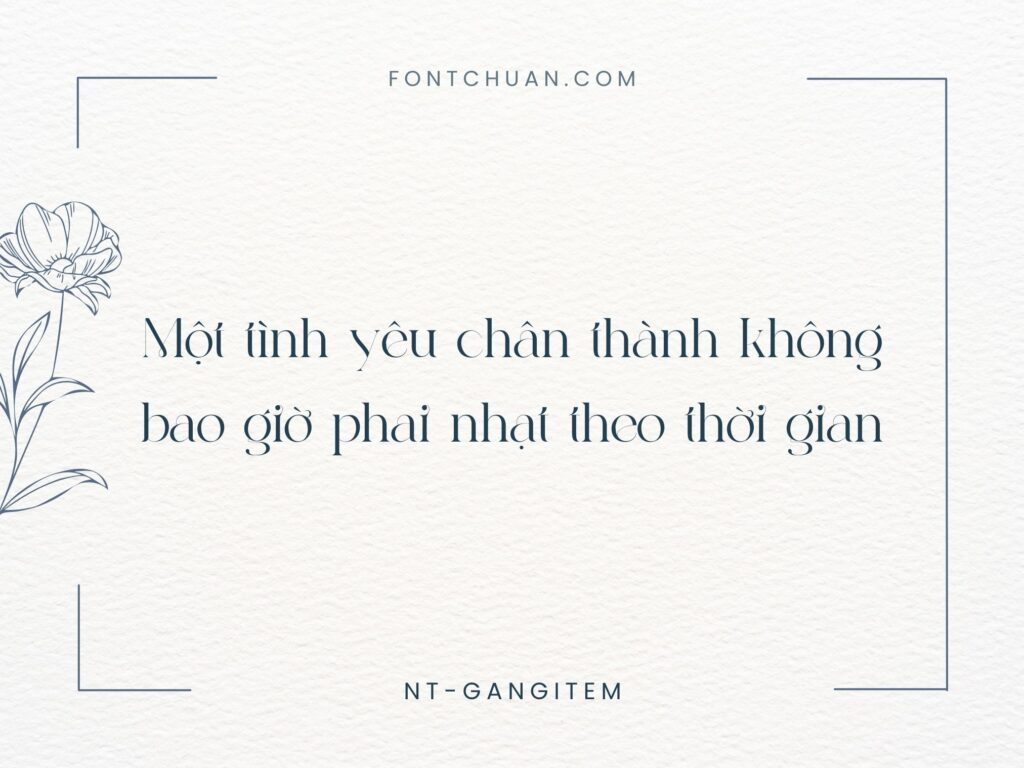
Font Gangitem Việt Hóa
Gangitem là một font serif hiện đại và thanh lịch, được thiết kế bởi 177Studio. Font này được trang bị nhiều ligature tùy ý, mang đến sự đa dạng và tinh tế trong thiết kế typography. Gangitem không chỉ là một Font Display lý tưởng cho các tiêu đề, logo, trích dẫn nổi bật mà còn có thể được sử dụng như một Font chữ thiệp cưới sang trọng, tạo vẻ đẹp tinh tế và lãng mạn cho các thiết kế thiệp mời, thiệp cưới hoặc các ấn phẩm sự kiện đặc biệt. Font này hỗ trợ tiếng Việt và nhiều ngôn ngữ khác, được sưu tầm và đăng bởi thành viên của Font Chuẩn.
Font có cấu trúc chữ rõ ràng, các đường nét tinh tế và độ dày nét đa dạng, tạo nên sự cân bằng giữa tính thẩm mỹ và khả năng đọc. Gangitem phù hợp cho các thiết kế thiệp mời, logo, tiêu đề và các ấn phẩm truyền thông. Các ngành nghề như quảng cáo, thiệp cưới, giáo dục và bất động sản có thể tận dụng hiệu quả font này. Ngoài ra, Gangitem cũng thích hợp cho các sự kiện như lễ hội, sinh nhật, ngày Nhà giáo và Valentine.